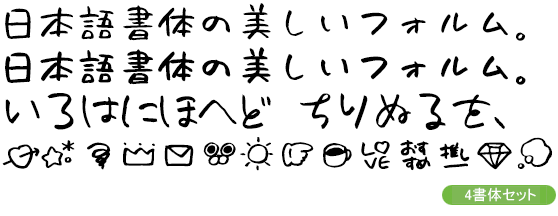
またたびフォント
『猫にまたたび、かいぬしお酒』をコンセプトに、よっぱらいのへろりとした文字をアナログで綴った日本語フォントです。またたびフォント、またたびフォントBold、またたびぷらす、またたびえもじのフォント4点と、おまけ素材としてフォントと組み合わせて使える書き下ろし手書きPNG素材60点(png)も同梱しています。
またたびフォント
またたびフォント・またたびフォントBold
またたびぷらす
またたびえもじ
・全ての文字を一文字ずつ筆ペンで書きました。正確な とめ・はらい には期待しないでください。(誤字ではありません)